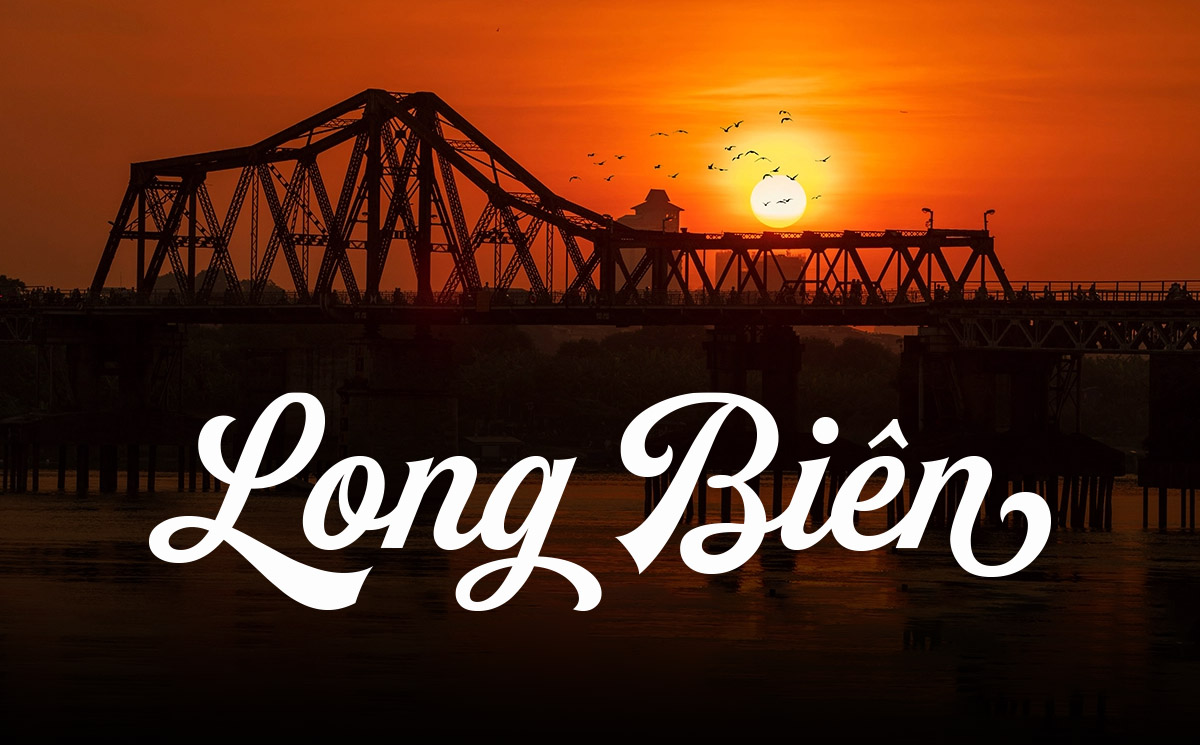
Nếu bạn đang tìm kiếm một bộ font chữ vừa mang nét cổ điển quyến rũ, vừa thể hiện sự mềm mại trong từng đường nét viết tay thì SVN Buinton chính là sự lựa chọn tuyệt vời không thể bỏ qua. Đây là bản font chữ Việt hóa cao cấp, được chế tác tỉ mỉ nhằm đáp ứng nhu cầu sáng tạo đa dạng của các thiết kế đồ họa tại Việt Nam. Với sự kết hợp hoàn hảo giữa phong cách retro hoài cổ và nét chữ nắn ngót tự nhiên, bộ font này hứa hẹn sẽ mang đến sức sống mới và đẳng cấp vượt trội cho mọi dự án của bạn.
Font Chữ Viết Tay Mềm Mại Phong Cách Vintage SVN Buinton – Font Chữ Việt Hóa Đỉnh Cao Cho Thiết Kế
Trong thế giới thiết kế đồ họa đương đại, xu hướng vintage và retro luôn giữ một vị trí vô cùng đặc biệt trong lòng người thưởng thức. Việc lựa chọn một typography phù hợp để truyền tải trọn vẹn linh hồn hoài niệm của phong cách này là yếu tố quyết định sự thành bại của một tác phẩm. Font chữ viết tay mềm mại phong cách vintage SVN Buinton ra đời như một giải pháp hoàn hảo, kết hợp tinh tế giữa vẻ đẹp cổ điển sang trọng và tính ứng dụng linh hoạt. Phiên bản Việt hóa chỉn chu giúp người dùng dễ dàng thao tác bằng tiếng Việt mà không gặp bất kỳ lỗi font hay lệch dấu nào.
1. Đường nét nét chữ uốn lượn mềm mại đậm chất vintage cổ điển
SVN Buinton nổi bật với cấu trúc chữ nắn ngót, lấy cảm hứng từ kỹ thuật vẽ chữ bảng hiệu (script signage) nổi tiếng của các thập niên trước. Các đường nét được tạo hình nhịp nhàng, uốn lượn tự nhiên giống như những dòng chữ được viết bằng ngòi bút mực truyền thống của các nghệ nhân calligraphy.
Điểm độc đáo của font chữ này nằm ở sự cân bằng tuyệt vời giữa nét thanh và nét đậm. Sự chuyển nhịp mượt mà giữa các nét chữ không chỉ tạo nên hiệu ứng thị giác mạnh mẽ mà còn mang đến cảm giác ấm áp, gần gũi và vô cùng lãng mạn cho các sản phẩm truyền thông thị giác.
2. Bộ ký tự Việt hóa hoàn chỉnh chuẩn Unicode với hệ thống dấu thanh tối ưu
Để phục vụ tốt nhất cho cộng đồng thiết kế tại Việt Nam, SVN Buinton đã được Việt hóa toàn bộ bảng ký tự theo chuẩn Unicode. Quá trình Việt hóa được thực hiện tỉ mỉ, đảm bảo giữ nguyên giá trị thẩm mỹ ban đầu của font chữ gốc.
- Dấu thanh sắp xếp chuẩn xác: Các dấu hỏi, ngã, sắc, huyền, nặng cùng các dấu phụ (â, ê, ô, ơ, ư, đ) được tinh chỉnh kích thước và vị trí hợp lý, không làm đè nét hay phá vỡ cấu trúc tổng thể của chữ.
- Khắc phục triệt để lỗi hiển thị: Bạn có thể tự tin soạn thảo các đoạn văn bản tiếng Việt từ ngắn đến dài mà không gặp hiện tượng mất ký tự hay gõ ra các ký tự ô vuông vô nghĩa.
3. Tích hợp tính năng OpenType phong phú với các ký tự thay thế và nét trang trí (Swashes)
Sự đa dạng trong khả năng tùy biến chính là lý do giúp SVN Buinton chiếm trọn tình cảm của các designer. Font được trang bị hệ thống OpenType thông minh, cung cấp hàng loạt ký tự thay thế (Alternates) và ký tự nối (Ligatures) độc đáo.
Người dùng có thể dễ dàng chèn các đuôi chữ uốn lượn (swashes) ở đầu hoặc cuối từ để tạo điểm nhấn nghệ thuật ấn tượng. Những đường nét trang trí này giúp dòng chữ trở nên sinh động, bay bổng hơn, loại bỏ hoàn toàn cảm giác thô cứng thường thấy ở các font chữ kỹ thuật số thông thường.
4. Ứng dụng linh hoạt và đa dạng trên nhiều sản phẩm thiết kế đồ họa
Nhờ vẻ đẹp vượt thời gian và tính thẩm mỹ cao, font chữ viết tay phong cách vintage SVN Buinton có thể ứng dụng hoàn hảo trong nhiều lĩnh vực sáng tạo khác nhau:
- Thiết kế nhận diện thương hiệu: Rất thích hợp để thiết kế logo, slogan cho các quán cà phê phong cách retro, tiệm bánh ngọt, tiệm cắt tóc barbershop, cửa hàng thời trang vintage hoặc sản phẩm thủ công handmade.
- Bao bì và nhãn mác sản phẩm: Tạo nên sự sang trọng và độc đáo cho nhãn chai rượu, bao bì cà phê, hộp trà, mỹ phẩm thiên nhiên hay các sản phẩm quà tặng tinh tế.
- Ấn phẩm sự kiện và truyền thông: Hoàn hảo cho thiết kế thiệp cưới phong cách rustic, poster âm nhạc, bìa sách, áo phông, menu nhà hàng và các hình ảnh trích dẫn (quotes) nghệ thuật trên mạng xã hội.
5. Tối ưu hóa kỹ thuật hiển thị sắc nét từ bản in cho đến nền tảng số
SVN Buinton được tối ưu hóa kỹ lưỡng về mặt vector. Các đường cong (bezier curves) được xử lý mượt mà, số lượng điểm neo (anchor points) được tối giản giúp font chữ đạt độ sắc nét tuyệt đối khi hiển thị.
Dù bạn sử dụng font chữ này cho các ấn phẩm in ấn kích thước lớn như banner, billboard, hay in ấn chất lượng cao trên các chất liệu khắc gỗ, in lụa, cho đến các thiết kế hiển thị trên màn hình kỹ thuật số (website, ứng dụng di động, hình ảnh Social Media), font luôn giữ được độ chi tiết mượt mà và chân thực nhất.
Bí Quyết Phối Hợp Font SVN Buinton Cho Thiết Kế Ấn Tượng
Để khai thác tối đa vẻ đẹp của font chữ viết tay mềm mại phong cách vintage SVN Buinton, bạn có thể kết hợp một số mẹo bố cục và kết hợp chữ (font pairing) chuyên nghiệp dưới đây: <ol>
- Phối hợp tương phản: Sử dụng SVN Buinton cho các tiêu đề chính (Headings) để thu hút sự chú ý, kết hợp cùng một font chữ Sans-serif hiện đại đơn giản hoặc font Serif thanh lịch cho phần nội dung (Body text) để tạo sự cân bằng thị giác.